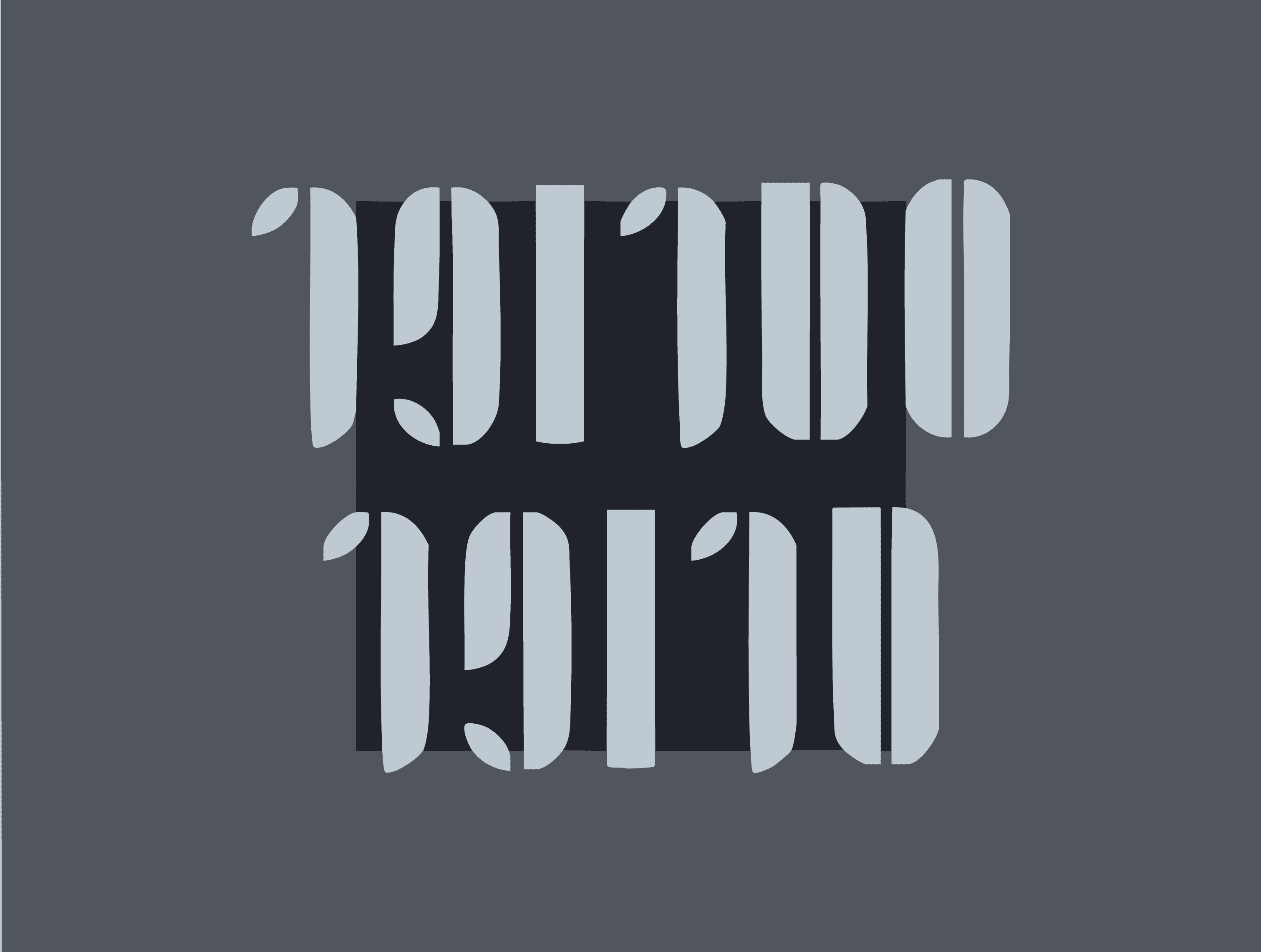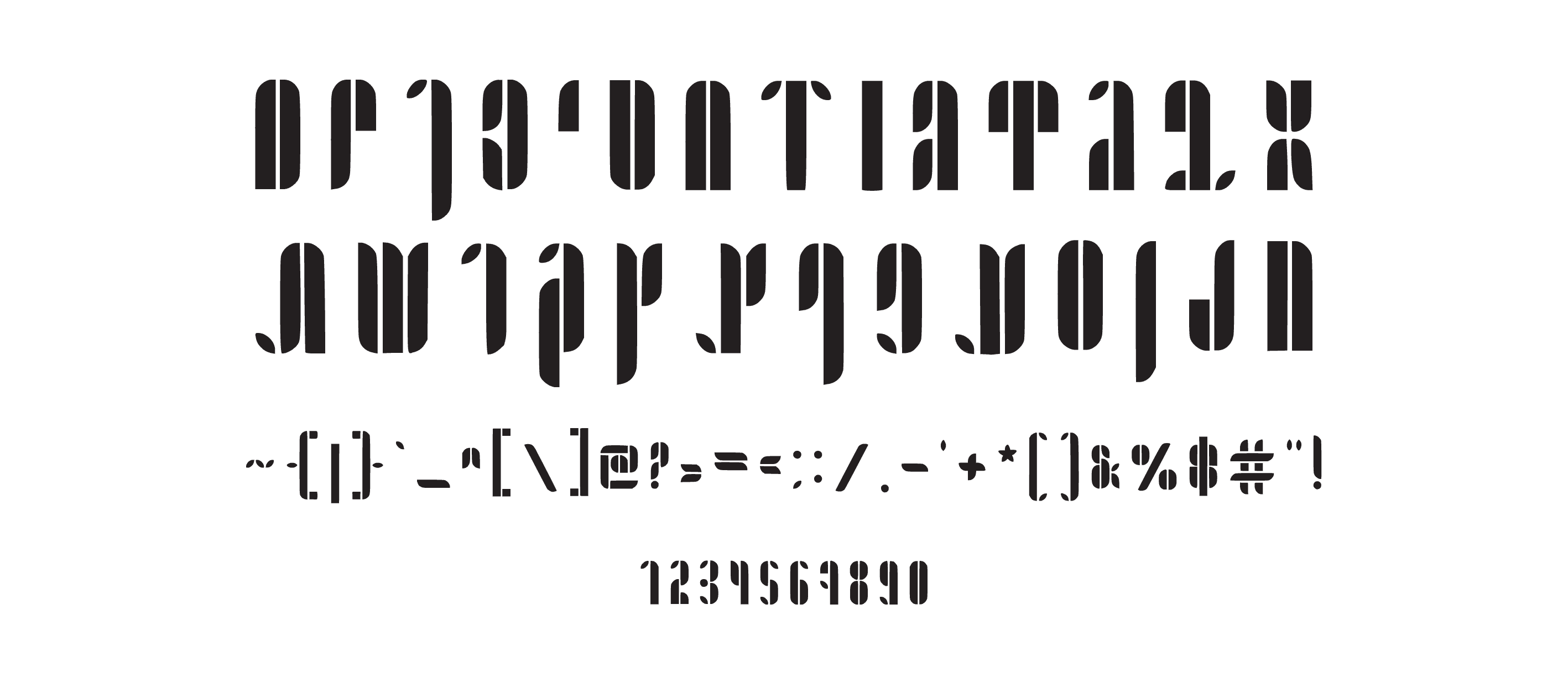
פונט סטרופר-טרופר
פונט עברי כבד וגרפי בסגנון מדע בדיוני ותעשייה עתידנית — מושלם לפוסטרים ולוגואים נועזים.
סטרופר טרופר — לא כל פונט נועד להיות ידידותי
אם יש פונט שלא מתנצל — זה הפונט הזה.
סטרופר טרופר הוא פונט עברי קשוח, עוצמתי ומדויק, שמשדר עוצמה תעשייתית וקרירה.
הוא בנוי מצורות גזורות חזקות, כמו שבלונות תעשייתיות או שריונות חלל — עם חלוקות גרפיות דרמטיות ומראה כמעט עתידני.
זהו פונט שלא בא לשחק, אלא ליצור אמירה חזקה ובלתי נשכחת — בכל כותרת, פוסטר או לוגו.
איפה הוא מרגיש בבית?
⚙️ פוסטרים גרפיים עוצמתיים
⚙️ עיצובים בהשראת מדע בדיוני
⚙️ לוגואים נועזים ותעשייתיים
⚙️ עולמות של משחקים, טכנולוגיה ועיצוב מחוספס
למי הוא מתאים?
למעצבים שמחפשים להביא עוצמה, ניכור גרפי ותעוזה ויזואלית חזקה לכל עיצוב.